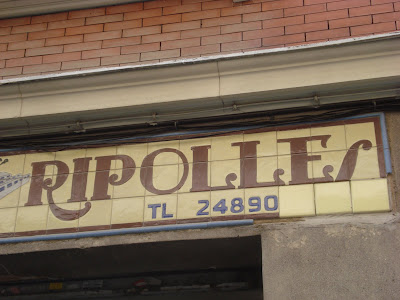
En la calle Castillo 22.
Abierta en la posguerra (años 40 del siglo XX), demuestra que los azulejos fabricados en Castellón ya gozaban de merecida fama entonces.
Se trata de un rótulo muy decorativo y castizo pero con una tipografía, como correspondía al ambiente de la época, que resulta tan anacrónica como folclórica.